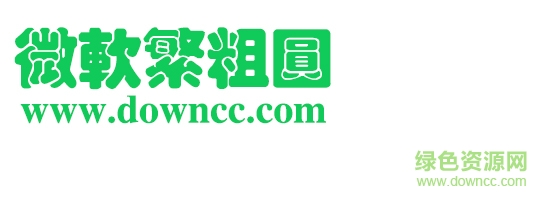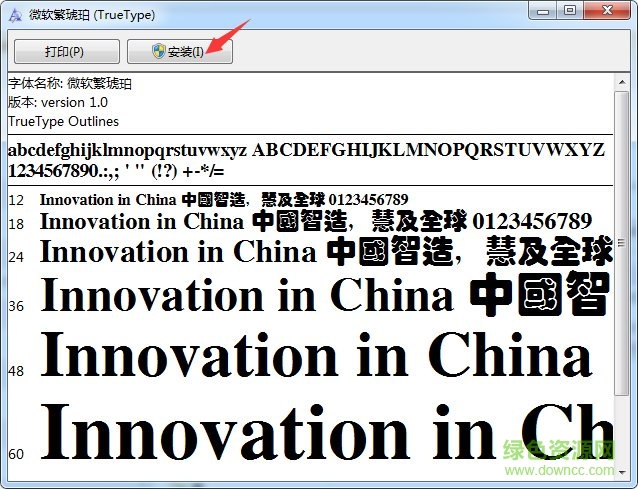
微軟繁琥珀字是微軟字體庫(kù)中的免費(fèi)字體資源,輸出的文字效果和簡(jiǎn)體琥珀一樣靈動(dòng)!支持中英文以及數(shù)字輸出。安裝完成后可以直接在ps或word軟件中打開(kāi)使用。歡迎在綠色資源網(wǎng)下載安裝。
微軟繁琥珀是一款藝術(shù)設(shè)計(jì)方面的中文簡(jiǎn)體漢字,字體剛勁有力,可應(yīng)用于繪畫(huà)設(shè)計(jì)、藝術(shù)創(chuàng)作、平面廣告、印刷包裝等領(lǐng)域!